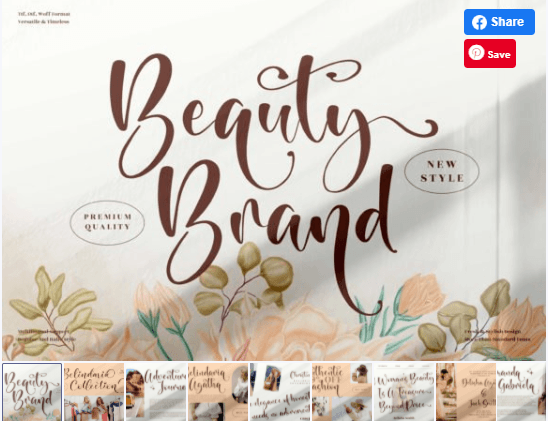
Beauty Brand Font
Beauty Brand - прекрасный и неподвластный времени рукописный шрифт. Это лучший выбор для создания привлекательных логотипов, брендов и цитат. Beauty Brand закодирован в кодировке PUA, что означает, что вы можете легко получить доступ ко всем глифам и росчеркам!